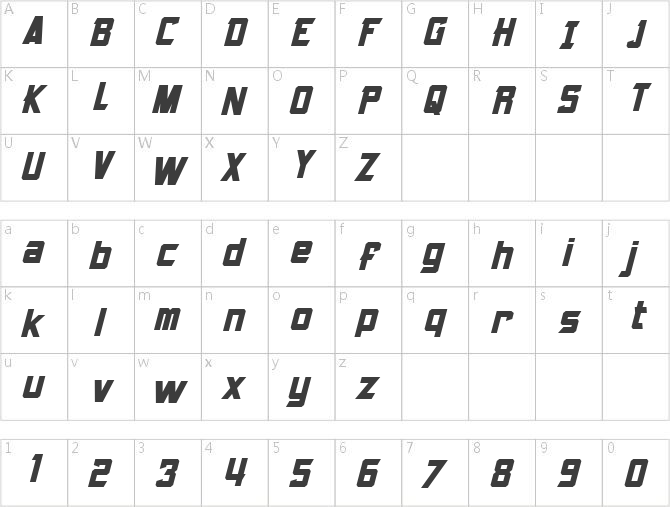
Armorhide Italic 詳情頁(yè)
Armorhide Italic字體字庫(kù)是一款讓人賞心悅目、百看不厭的英文字體,適合各類廣告和產(chǎn)品包裝設(shè)計(jì)應(yīng)用,字體大小0.02MB,格式為ttf字體,上傳用戶是lvpyt,作者/版權(quán)方為未知